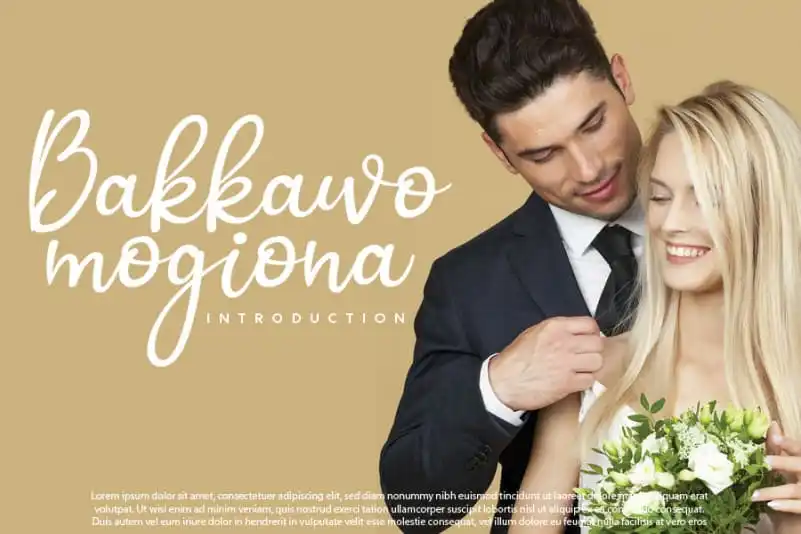
Bakkawo Calligraphy Font – Download Grátis
A Bakkawo Calligraphy Font é uma fonte criada a mão com um ar jovial e descontraído, cuidadosamente concebida para se tornar um grande favorito. Com seu charme casual, ela parece simpática e acessível, sendo perfeitamente legível e altamente versátil. Suas linhas elegantes e fluidas têm um toque de movimento leve que a torna única, capaz de dar vida às mais variadas propostas gráficas. Seja em ambientes muito coloridos ou como o centro de destaque de um layout complexo, esta fonte irá brilhar. Suavizaria textos informativos para uma aparência descontraída, ou transformaria mensagens importantes em uma explosão visual alegre e encorajadora. A Bakkawo Calligraphy Font está disponível no seu ateliê de letras como uma solução perfeita para designers gráficos que desejam adicionar um toque único e amigável às suas criações digitais.